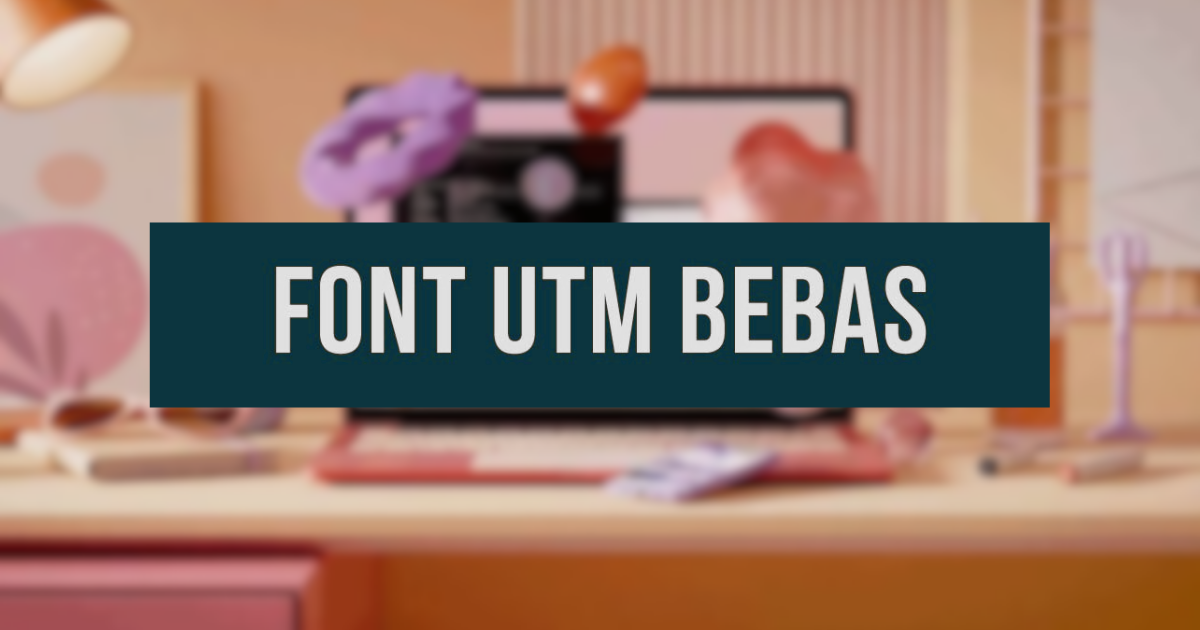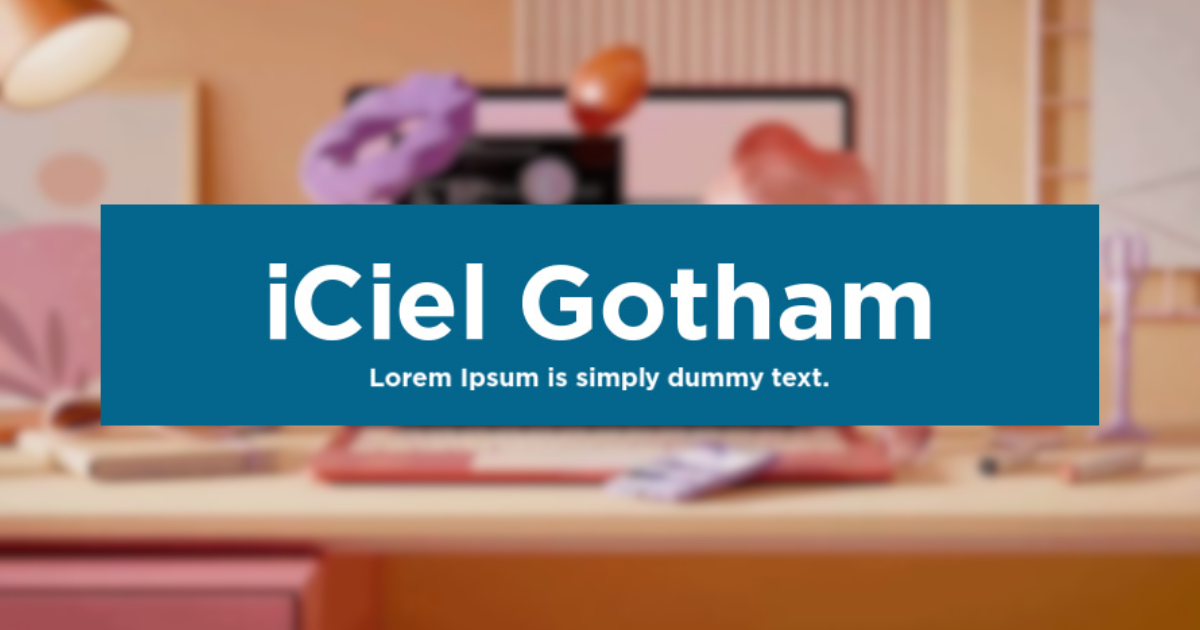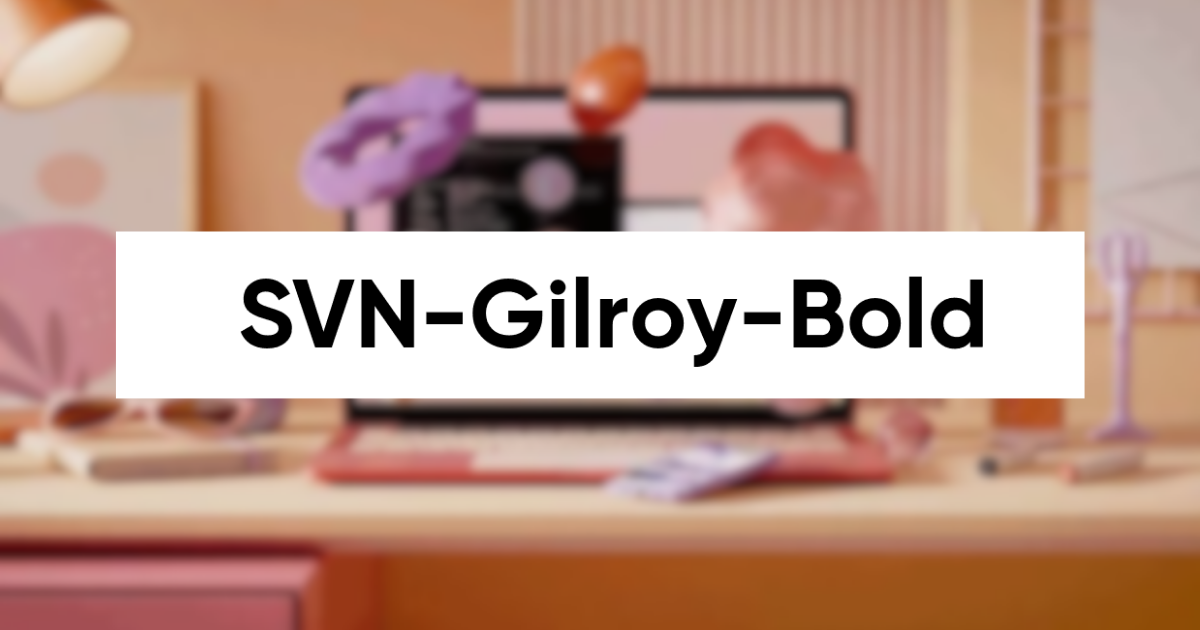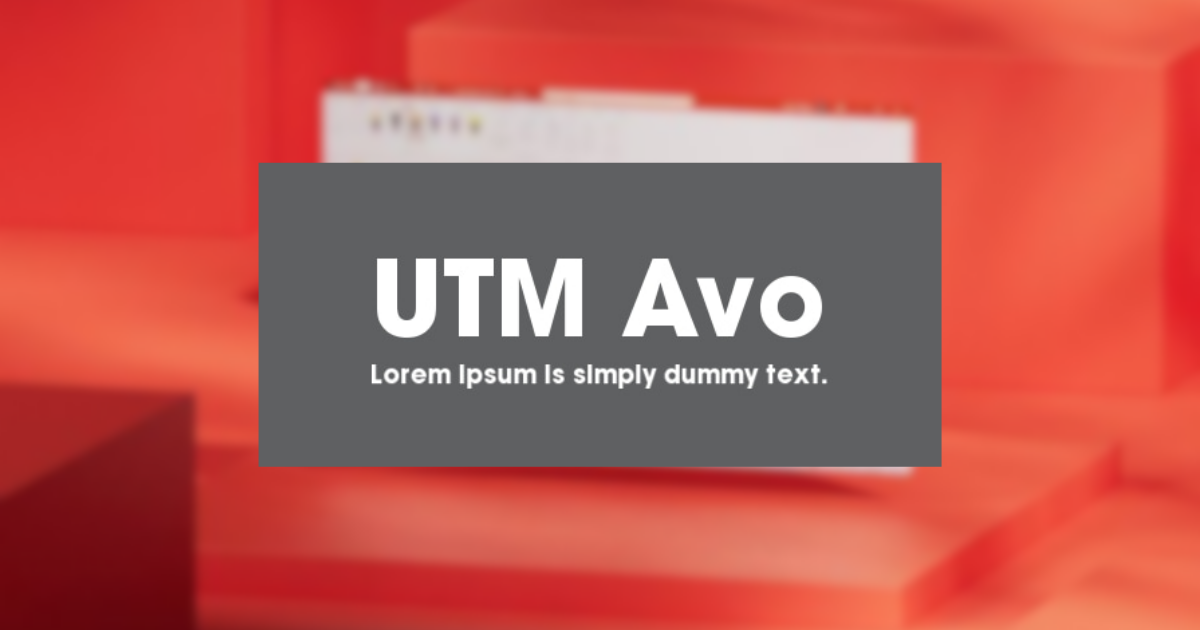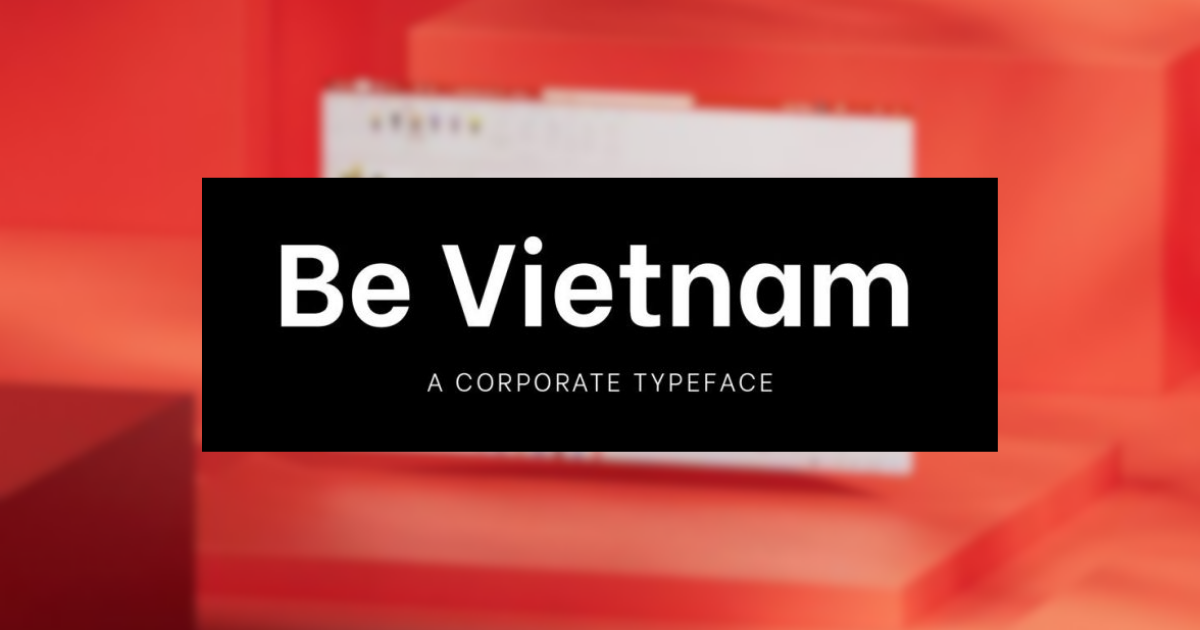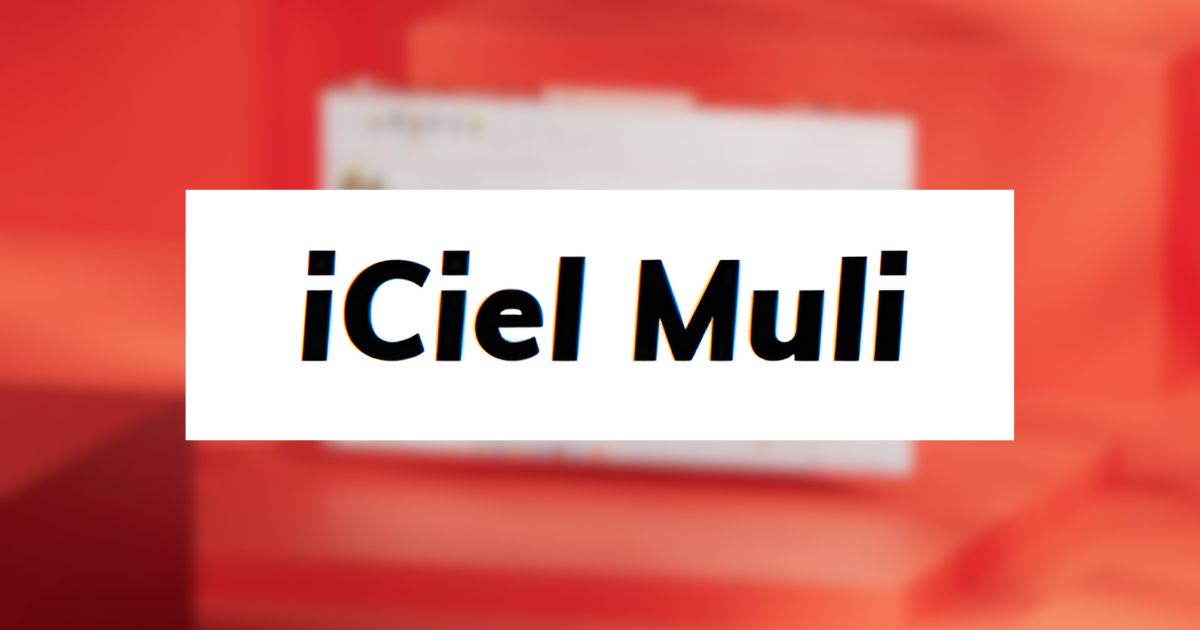
Top 10+ Font chữ đẹp cho PowerPoint giúp bài thuyết trình ấn tượng
Việc lựa chọn và sử dụng font chữ đẹp cho PowerPoint đóng vai trò then chốt trong việc tạo ra một bài thuyết trình chuyên nghiệp, giúp truyền tải thông điệp một cách hiệu quả và thu hút sự chú ý của khán giả ngay từ cái nhìn đầu tiên. Vì vậy, một file PowerPoint với bộ font chữ tinh tế không chỉ làm đẹp slide mà còn thể hiện tư duy thẩm mỹ và sự chỉn chu của người thuyết trình trong mọi dự án. Bên cạnh đó, còn tăng sự chú ý của người nghe đối với bài trình bày của người nói.
Tầm quan trọng của việc chọn font chữ đẹp cho PowerPoint
Trong thiết kế bài thuyết trình, font chữ không đơn thuần chỉ là phương tiện hiển thị văn bản mà còn là yếu tố định hình phong cách và cảm xúc của toàn bộ nội dung. Một bộ font chữ đẹp cho PowerPoint nên được lựa chọn kỹ lưỡng sẽ giúp người xem dễ dàng tiếp nhận thông tin, giảm bớt sự mệt mỏi cho mắt khi phải theo dõi các trang slide dài và đồng thời tạo ra sự kết nối về mặt thị giác giữa các nội dung trong slide.
Font chữ đẹp cho PowerPoint
Bên cạnh đó, việc sử dụng các font chữ đồng nhất và phù hợp với chủ đề sẽ giúp tăng cường tính nhận diện và sự chuyên nghiệp cho cá nhân hoặc tổ chức. Khi bạn biết cách phối hợp giữa các font chữ tiêu đề đẹp PowerPoint và font nội dung, bài thuyết trình của bạn sẽ trở nên có chiều sâu, minh bạch và có sức thuyết phục cao hơn đối với đối tác hoặc cấp trên trong các buổi họp quan trọng.
Tiêu chí lựa chọn font chữ PowerPoint thuyết trình chuyên nghiệp
Để tạo ra một bài trình chiếu hoàn hảo, việc lựa chọn font chữ đẹp cho PowerPoint cần tuân thủ những quy chuẩn thiết kế khắt khe nhằm đảm bảo tính thẩm mỹ và hiệu năng sử dụng. Dưới đây là những tiêu chí quan trọng nhất giúp bạn lọc ra được những bộ font chữ PowerPoint thuyết trình phù hợp nhất cho công việc của mình:
Font chữ đẹp cho PowerPoint
• Độ dễ đọc: Đây là yếu tố tiên quyết khi chọn font chữ cho bài thuyết trình vì khán giả thường đứng ở khoảng cách xa để theo dõi. Bạn nên ưu tiên những font chữ có khoảng cách giữa các ký tự rõ ràng, nét chữ không quá mảnh cũng không quá dày để đảm bảo nội dung luôn hiển thị sắc nét trên mọi loại màn hình máy chiếu hiện nay.
• Sự tương thích hệ thống: Một bộ font đẹp nhưng không có tính tương thích cao sẽ dễ dẫn đến tình trạng lỗi hiển thị khi chuyển file sang máy tính khác. Do đó, hãy cân nhắc chọn những font phổ biến hoặc nắm vững kỹ thuật nhúng font vào file để đảm bảo rằng toàn bộ định dạng văn bản của bạn được giữ nguyên vẹn dù trình chiếu ở bất cứ đâu.
• Phong cách phù hợp nội dung: Mỗi loại font chữ đều mang đặc trưng riêng, từ hiện đại, năng động đến cổ điển, trang trọng. Việc xác định rõ đối tượng khán giả và tính chất của buổi thuyết trình sẽ giúp bạn quyết định nên dùng font không chân (Sans Serif) cho các chủ đề công nghệ hay font có chân (Serif) cho các báo cáo mang tính học thuật cao.
Tổng hợp các font chữ đẹp trong PowerPoint phổ biến nhất hiện nay
Hiện nay, có rất nhiều bộ font được các chuyên gia thiết kế tin dùng để tạo nên những slide ấn tượng và hiện đại. Việc nắm bắt được danh sách các font chữ đẹp trong PowerPoint sẽ giúp bạn tiết kiệm thời gian tìm kiếm và tập trung hơn vào việc sáng tạo nội dung chất lượng. Dưới đây sẽ là một số những gợi ý hàng đầu:
Nhóm font chữ Sans Serif (không chân) hiện đại
Nhóm font chữ Sans Serif hay còn gọi là font không chân, đang trở thành xu hướng chủ đạo trong thiết kế slide hiện đại nhờ vẻ ngoài tối giản và tinh tế. Đặc điểm nổi bật của nhóm này là các đường nét gọn gàng, không có các chi tiết thừa ở đầu ký tự, giúp tối ưu hóa khả năng hiển thị trên các màn hình kỹ thuật số độ phân giải cao. Việc sử dụng font không chân giúp bài thuyết trình của bạn trông thoáng đãng, chuyên nghiệp và cực kỳ dễ theo dõi đối với mọi khán giả.
• Montserrat: Đây là một trong những font chữ quốc dân được yêu thích nhất nhờ vẻ ngoài hiện đại, mạnh mẽ và cực kỳ dễ đọc. Montserrat có nhiều định dạng từ cực mảnh đến rất đậm, giúp bạn dễ dàng tùy biến cho cả tiêu đề lẫn nội dung chi tiết mà vẫn đảm bảo được sự đồng bộ và tinh tế cho toàn bộ trang slide.
Font chữ đẹp cho PowerPoint
• Roboto: Được phát triển bởi Google, Roboto mang lại cảm giác thân thiện, chuyên nghiệp và rất tối ưu cho các thiết bị kỹ thuật số. Font chữ này có cấu trúc hình học rõ ràng nhưng vẫn giữ được những đường cong mềm mại, tạo nên một tổng thể hài hòa và hiện đại, rất phù hợp cho các bài thuyết trình về công nghệ hoặc marketing.
Font chữ đẹp cho PowerPoint
• Open Sans: Với phong cách tối giản và thanh lịch, Open Sans là sự lựa chọn tuyệt vời cho những ai muốn bài thuyết trình của mình trông thật chuyên nghiệp. Điểm mạnh của font này là sự cân bằng tuyệt đối giữa các nét chữ, giúp khán giả có thể đọc nội dung trong thời gian dài mà không cảm thấy mỏi mắt hay khó chịu.
Font chữ đẹp cho PowerPoint
• Lato: Lato mang đến một sự pha trộn độc đáo giữa sự cứng cáp và các đường nét ấm áp, tạo cảm giác tin cậy cho người xem. Đây là font chữ thường được dùng trong các bài thuyết trình doanh nghiệp hoặc giới thiệu dự án, nơi mà sự chuyên nghiệp và tính minh bạch luôn được đặt lên hàng đầu trong thiết kế.